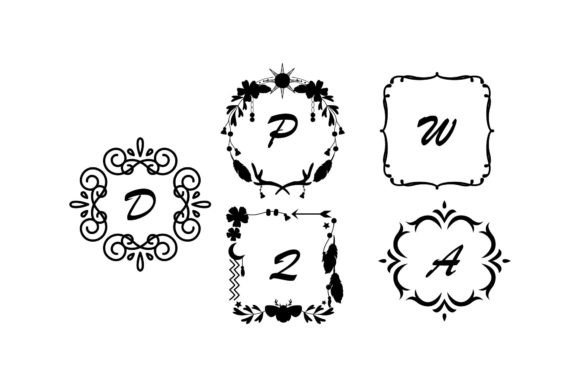
Monogram Font Set
適切なデザイン要素を見つけるのは難しい場合がありますが、Monogram Font Setは作品を即座に引き立てる優れたコレクションを提供します。
POD(オンデマンド印刷)製品、結婚式の招待状、またはソーシャルメディアのグラフィックを作成している場合でも、Monogram Font Setは理想的です。